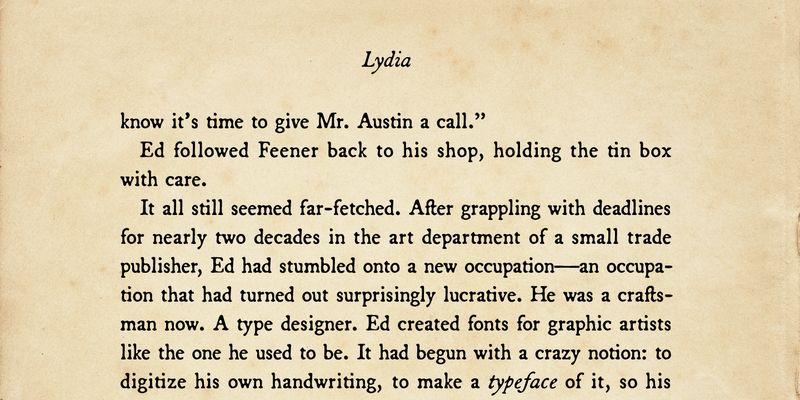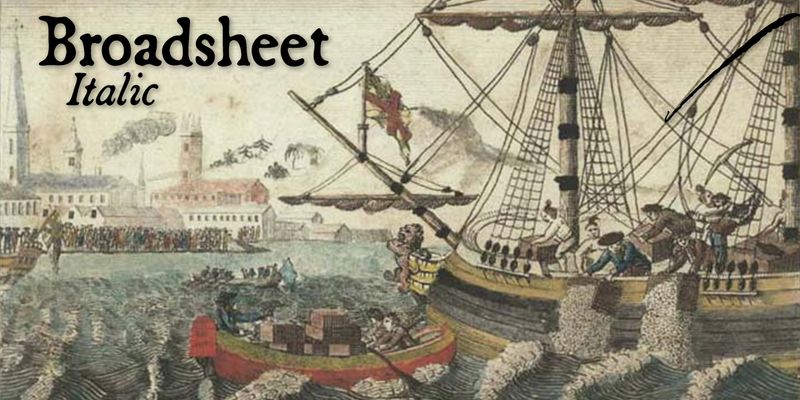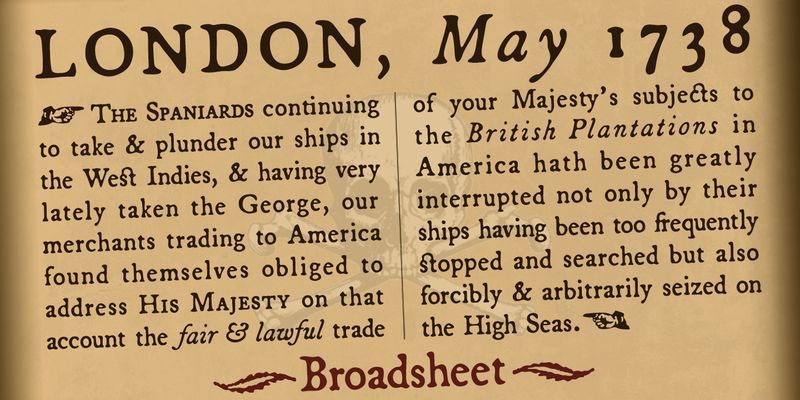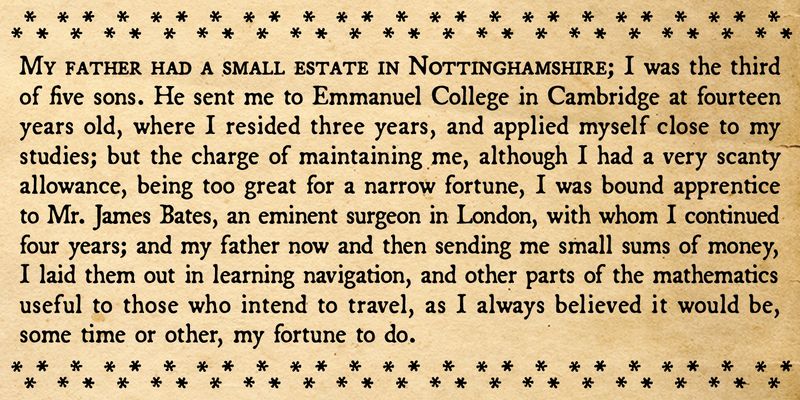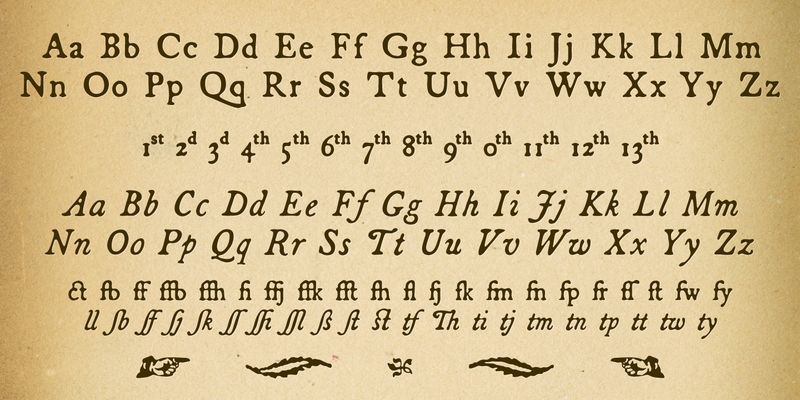
Broadsheet™ est modelé d’après les caractères des journaux américains coloniaux. Ses styles romain et italique comportent des dizaines de ligatures, de véritables petites capitales, quelques ornements d’imprimeur et un support complet du latin.